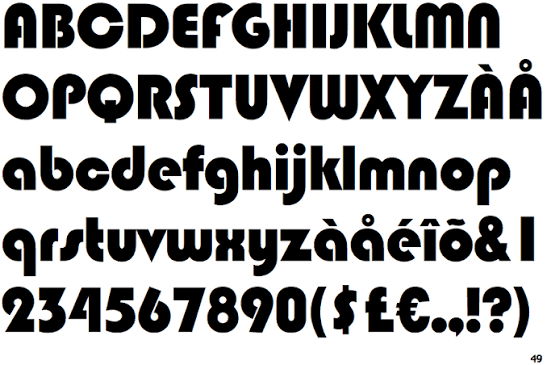
Nhiều designer gặp khó khăn khi tìm Font Blippo Việt hóa phù hợp, thường xảy ra lỗi thiếu dấu tiếng Việt hoặc các đường nét bo tròn bị mất chi tiết khi phóng lớn để in trên bao bì sản phẩm. Những lỗi kỹ thuật này khiến thiết kế mất đi sự mềm mại, thân thiện và làm giảm tính chuyên nghiệp của hình ảnh thương hiệu.
Font Blippo là gì?
Font Blippo là một phông chữ thuộc dòng Display mang phong cách bong bóng, tròn trịa và vui tươi. Đặc trưng của Blippo là các đường nét dày dặn, không có chân và các góc bo tròn tối đa, tạo cảm giác thân thiện, hoài cổ và dễ gần cho người xem. Đây là lựa chọn quen thuộc cho các thiết kế bao bì thực phẩm trẻ em, biển hiệu cửa hàng, nhãn dán sản phẩm hoặc các ấn phẩm truyền thông mang lại năng lượng tích cực.
Ưu điểm nổi bật của bộ phông này là khả năng tạo hiệu ứng thị giác đáng yêu ngay từ cái nhìn đầu tiên. Bộ phông hỗ trợ tốt cho việc làm nổi bật tiêu đề chính trong các bố cục sáng tạo. Bản Font Blippo Việt hóa do In Viva cung cấp đã được căn chỉnh kerning cẩn thận, giúp các nhà thiết kế tự tin ứng dụng vào các dự án thương mại tại thị trường Việt Nam mà không lo lỗi hiển thị.
Bảng kí tự font Blippo
5 ứng dụng Font Blippo Việt hóa trong thiết kế và in ấn
Với đặc điểm chữ tròn, dày và mang phong cách Retro vui tươi, Font Blippo Việt hóa được ứng dụng linh hoạt trong nhiều sản phẩm bao bì, tem nhãn và quà tặng doanh nghiệp theo hướng trẻ trung, sáng tạo:
• Thiết kế bao bì bánh kẹo và thực phẩm trẻ em: Font Blippo phù hợp để thể hiện tên thương hiệu, tên sản phẩm trên hộp giấy, túi đựng bánh hoặc nhãn dán thực phẩm. Đường nét bo tròn giúp bao bì tạo cảm giác thân thiện, vui nhộn và dễ thu hút trẻ nhỏ.
• Sản xuất hộp quà tặng và sản phẩm phong cách Retro: Khi kết hợp cùng kỹ thuật in UV, ép kim màu hoặc phủ UV định hình, Font Blippo giúp các mẫu hộp quà, hộp giấy sáng tạo mang nét hoài cổ nhưng vẫn hiện đại, phù hợp với nhiều dòng sản phẩm lifestyle.
• In ấn túi giấy thương hiệu thời trang và giải trí: Logo hoặc slogan sử dụng Font Blippo trên túi giấy Kraft, Ivory hoặc giấy mỹ thuật giúp thương hiệu tạo dấu ấn riêng, thể hiện phong cách trẻ trung và gần gũi với khách hàng.
• Trang trí backdrop, poster và ấn phẩm sự kiện: Kiểu chữ có độ nhận diện cao giúp các tiêu đề chương trình, banner quảng cáo hoặc khu vực trưng bày trở nên nổi bật, đặc biệt phù hợp với các sự kiện dành cho giới trẻ, trẻ em.
• Sản xuất tem nhãn decal dán sản phẩm: Nhờ cấu trúc chữ dày và rõ nét, Font Blippo giúp tên sản phẩm nổi bật trên nhãn chai, hộp giấy hoặc bao bì bán lẻ, hỗ trợ khách hàng dễ dàng nhận diện thương hiệu.
Font Blippo đẹp 01
4 lưu ý khi sử dụng Font Blippo Việt hóa
Để Font Blippo Việt hóa giữ được vẻ đẹp đặc trưng và đảm bảo độ sắc nét khi in thực tế, designer cần chú ý:
• Kiểm soát độ dày nét chữ: Font Blippo có cấu trúc chữ khá dày, vì vậy nên cân chỉnh kích thước và khoảng cách ký tự phù hợp. Với các nội dung nhỏ dưới 12pt, cần kiểm tra trước để tránh tình trạng các nét bị dính vào nhau khi in.
• Tối ưu đường Path khi gia công dập nổi: Khi sử dụng Font Blippo làm logo trên hộp quà cao cấp, các đường cong bo tròn cần được xử lý vector sạch, loại bỏ điểm neo thừa để khuôn dập nổi thể hiện rõ hình dạng chữ và hạn chế lỗi răng cưa.
• Lựa chọn màu sắc in phù hợp: Font Blippo thường phát huy hiệu quả với các gam màu tươi sáng như vàng, đỏ, xanh pastel hoặc các màu tương phản cao. Việc kiểm tra hệ màu CMYK trước khi in giúp chữ giữ được độ nổi bật trên bao bì.
• Convert font trước khi gửi file sản xuất: Trước khi xuất file in, designer nên chuyển đổi Font Blippo thành dạng vector bằng lệnh Create Outlines để tránh lỗi thiếu font, sai ký tự hoặc thay đổi kiểu chữ khi mở trên hệ thống khác.